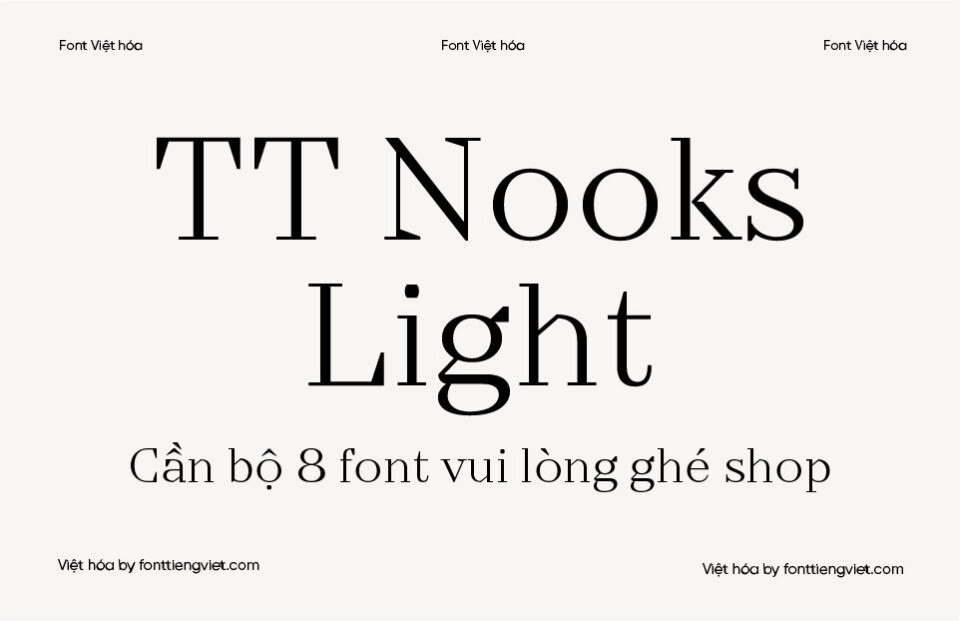
Font Việt hóa 1FTV VIP TT Nooks Light
Giới thiệu về Font Việt hóa 1FTV VIP TT Nooks Light
Trong thế giới thiết kế đồ họa hiện đại, việc lựa chọn một bộ Font Miễn Phí chất lượng luôn là ưu tiên hàng đầu của các nhà sáng tạo. Đặc biệt đối với những ai yêu thích phong cách thanh lịch và tinh tế, Font Việt hóa 1FTV VIP TT Nooks Light chính là sự lựa chọn không thể bỏ qua. Đây là một phông chữ thuộc trường phái Serif hiện đại, nổi bật với các đường nét mảnh mai nhưng vô cùng sắc sảo. Được đội ngũ 1FTV thực hiện việt hóa tỉ mỉ, bộ font này đảm bảo hiển thị hoàn hảo các dấu tiếng Việt mà không xảy ra tình trạng lỗi chân hay mất nét, mang lại sự chuyên nghiệp tối đa cho mọi bản thiết kế của người dùng Việt Nam.
Đặc điểm thiết kế của bộ font chữ
Lý do khiến Font Việt hóa 1FTV VIP TT Nooks Light trở nên khác biệt chính là cấu trúc hình học độc đáo kết hợp cùng các chi tiết cách điệu nhẹ nhàng. Với độ dày nét ở mức “Light”, phông chữ này tạo cảm giác không gian thoáng đãng, dễ đọc ngay cả ở kích thước nhỏ. Các ký tự được thiết kế với khoảng cách đồng đều, tạo nên sự cân bằng thị giác tuyệt vời. Điều này giúp bộ font cực kỳ phù hợp cho các tiêu đề tạp chí, bao bì sản phẩm cao cấp hoặc các thiệp mời sự kiện trang trọng. Sự thanh thoát của nó giúp nâng tầm giá trị thẩm mỹ cho tác phẩm mà không gây cảm giác nặng nề cho người xem.
Tại sao nên sử dụng Font Việt hóa 1FTV VIP TT Nooks Light trong thiết kế?
Khi thực hiện các dự án thiết kế, tính tương thích và ứng dụng đa dạng luôn được đặt lên bàn cân. Bộ Font Việt hóa 1FTV VIP TT Nooks Light đáp ứng xuất sắc cả hai tiêu chí này nhờ vào bộ mã ký tự đầy đủ và phong cách vượt thời gian.
Ứng dụng trong các dự án đồ họa chuyên nghiệp
Bạn có thể dễ dàng bắt gặp sự hiện diện của phông chữ này trong các bộ nhận diện thương hiệu của ngành thời trang, mỹ phẩm hoặc trang trí nội thất. Nhờ tính chất sang trọng vốn có, nó giúp truyền tải thông điệp về sự đẳng cấp và hiện đại một cách tự nhiên nhất. Bên cạnh đó, các blogger và người sáng tạo nội dung trên mạng xã hội cũng thường xuyên sử dụng bộ font này để làm Quotes hoặc thiết kế ảnh bìa để thu hút sự chú ý của độc giả ngay từ cái nhìn đầu tiên. Khả năng tùy biến linh hoạt cho phép bạn kết hợp nó với các font không chân (Sans-serif) để tạo ra sự tương phản đầy ấn tượng.
Tối ưu hóa hiển thị trên nền tảng kỹ thuật số
Không chỉ mạnh về in ấn, Font Việt hóa 1FTV VIP TT Nooks Light còn được tối ưu hóa để hiển thị sắc nét trên các thiết bị kỹ thuật số. Cho dù bạn đang thiết kế giao diện website hay trình bày bài giảng điện tử, phông chữ này vẫn giữ vững được hình khối và độ rõ ràng của từng chữ cái. Điều này cực kỳ quan trọng đối với các bạn học sinh và giáo viên khi cần tạo ra những tài liệu học tập vừa đẹp mắt vừa dễ tiếp cận thông tin, giúp quá trình truyền tải kiến thức trở nên sinh động và hiệu quả hơn rất nhiều.
Kết luận về giá trị của phông chữ việt hóa
Việc sở hữu một bộ font đẹp không chỉ giúp công việc thiết kế trở nên dễ dàng mà còn thể hiện gu thẩm mỹ tinh tế của người thực hiện. Với sự kết hợp giữa nét đẹp cổ điển và hơi thở hiện đại, đây chắc chắn là công cụ đắc lực cho mọi ý tưởng sáng tạo. Nếu bạn đang tìm kiếm sự khác biệt cho dự án tiếp theo, đừng ngần ngại lựa chọn Font Miễn Phí, Font Việt Hóa, Font Việt hóa 1FTV VIP TT Nooks Light để cảm nhận sự thay đổi rõ rệt trong từng đường nét. Hãy tải về ngay hôm nay và bắt đầu hành trình sáng tạo những tác phẩm nghệ thuật độc đáo của riêng mình!